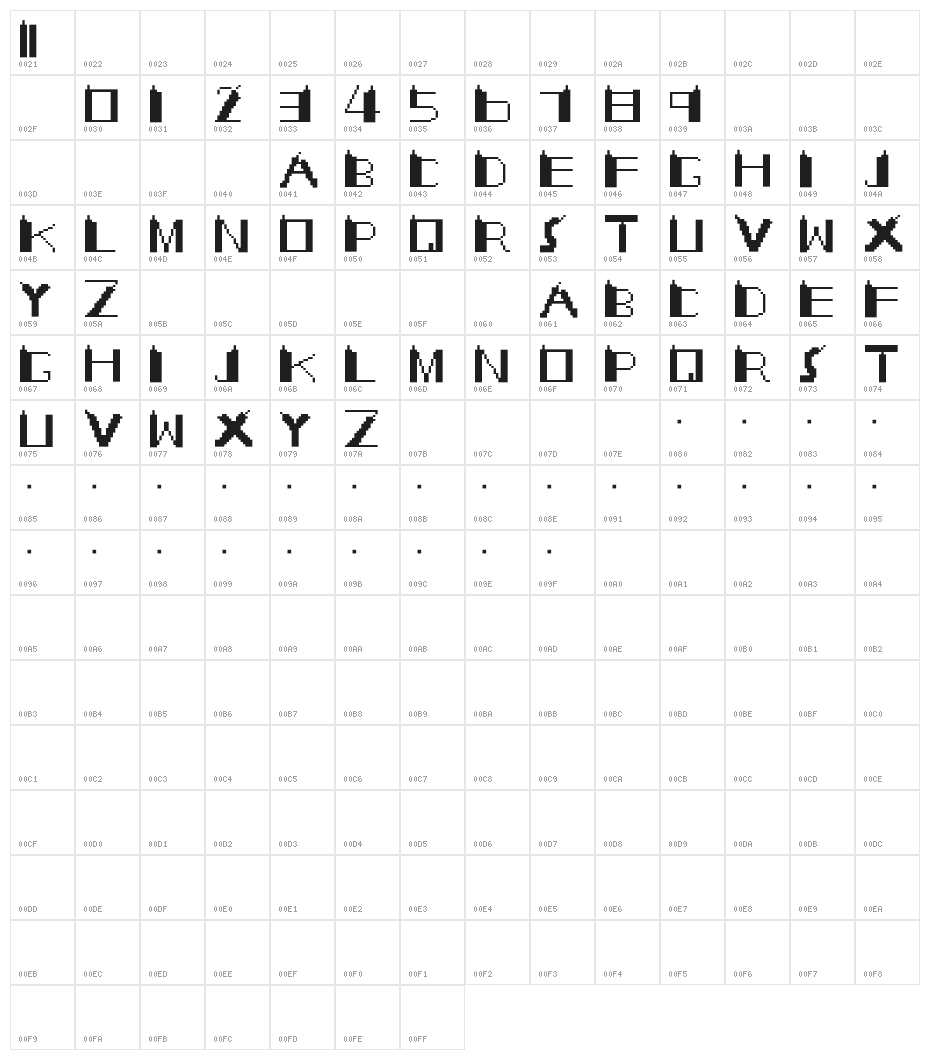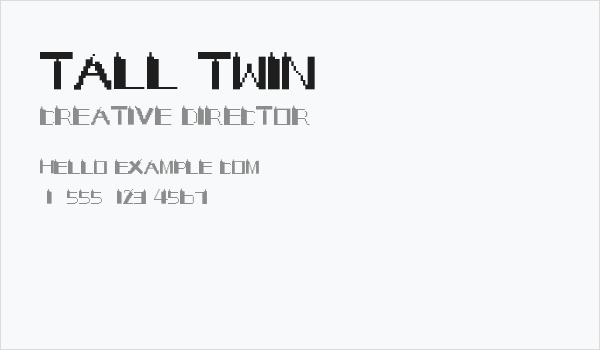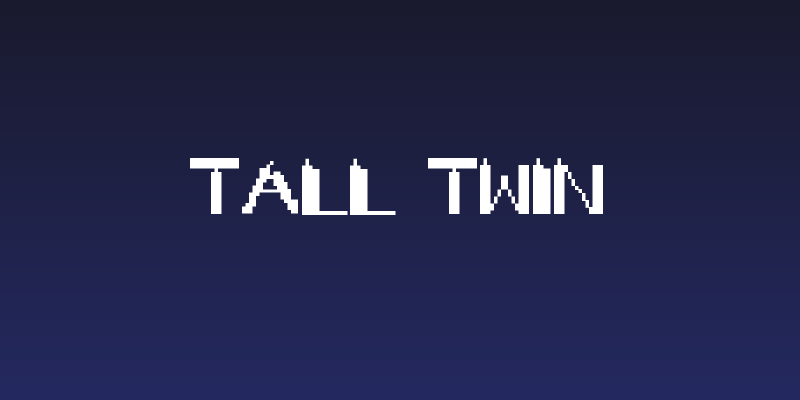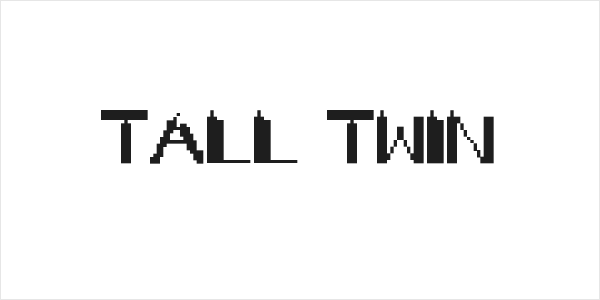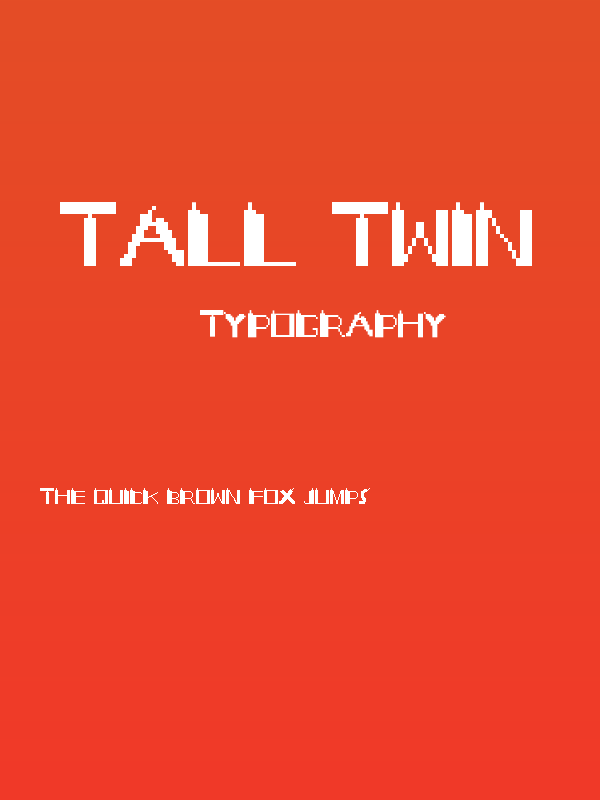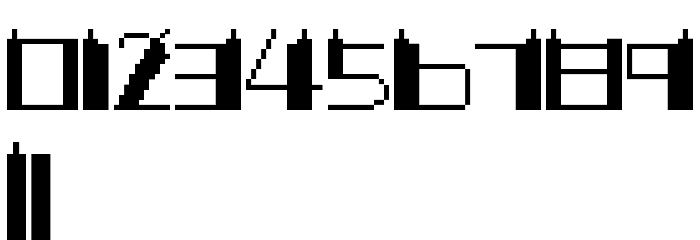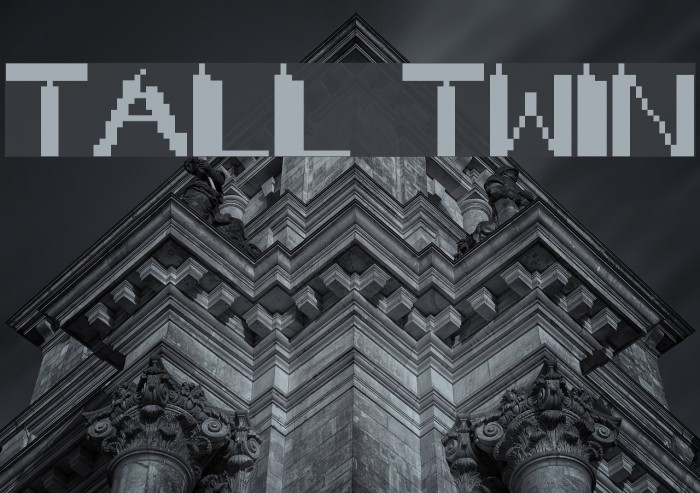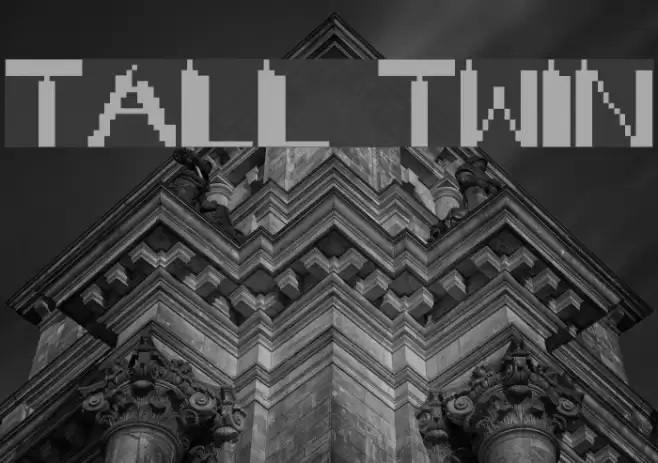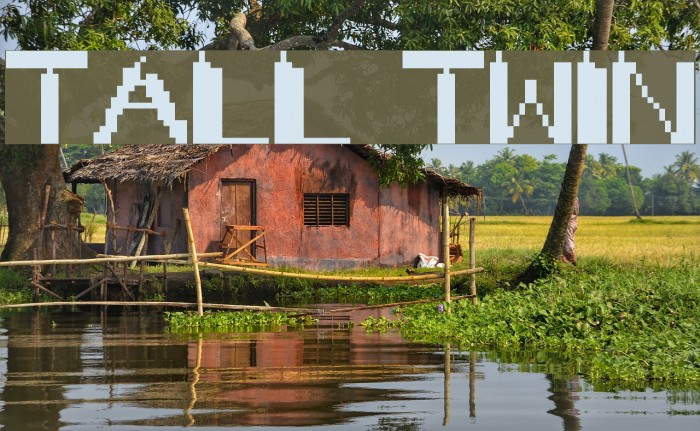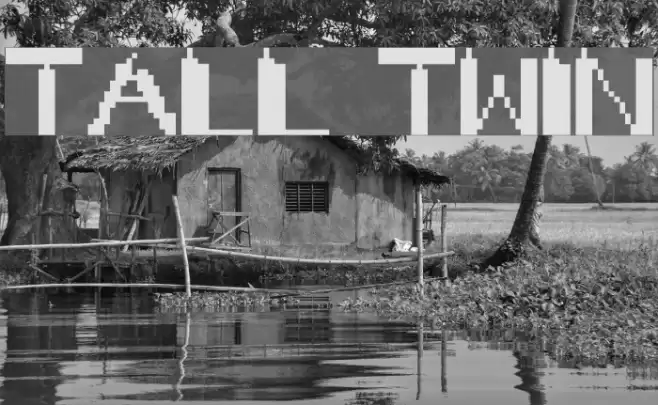
TALL TWIN Font
✎ Pixel
| Anwendungsfall | Logos, Headlines, Digital Art |
| Vorgeschlagene Projekte | Ideal for digital art, video game design, tech-themed posters, and modern branding. |